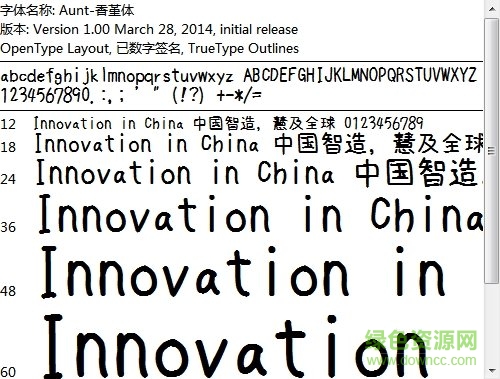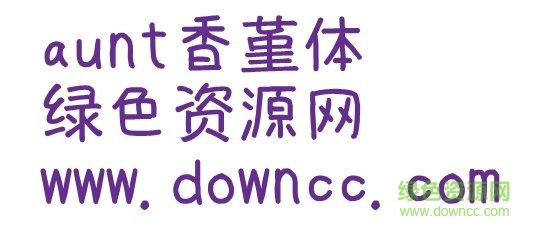
Aunt一品香堇體字體
香堇體是aunt系列最活潑清新的一款字體,也叫一品香堇體,筆畫(huà)干凈整齊,給人舒適純粹的閱讀好感,沒(méi)有多余的點(diǎn)綴,畫(huà)風(fēng)更加清爽得體,喜歡就來(lái)綠色資源網(wǎng)免費(fèi)體驗(yàn)吧!
aunt香堇體字體特色
一品香堇體是一款手寫(xiě)風(fēng)格的卡通字體,字體略帶稚氣,非常具有趣味性,尤其是設(shè)計(jì)完成之后的整體效果更是出眾,可廣泛應(yīng)用于平面設(shè)計(jì)、廣告設(shè)計(jì)、報(bào)紙雜志、正文標(biāo)題等領(lǐng)域!
一品香堇體字形大方得體,呈卡通風(fēng)格,整體效果十分出眾,是一款應(yīng)用于平面設(shè)計(jì)方面的簡(jiǎn)體中文字體!